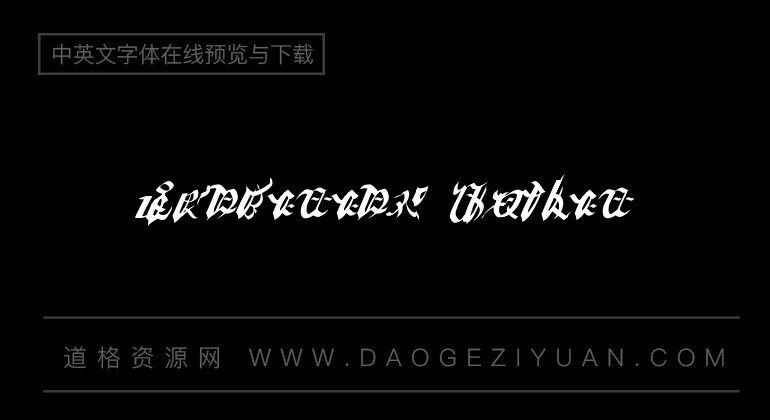
Ivalician Gothic 是一种活跃的、复古风格的字体,它源自古老的日本伊瓦利斯文字(Ivalician),可以说是一种混合着日本和西方文字的字体。它具有细腻的笔画,深沉的线条,以及日本传统的精细处理,使用它可以给文字带来深沉和优雅的气质。Ivalician Gothic 字体可以用于创作海报、广告、标志、标题和其他设计,可以给设计带来一种独特的复古风格。内容介绍
Ivalician Gothic是一款非常不错的手写艺术字体,具有很好的视觉感,适合于文化类的宣传设计、商业类品牌的广告和产品包装设计以及个性化文字排版等较多场景。